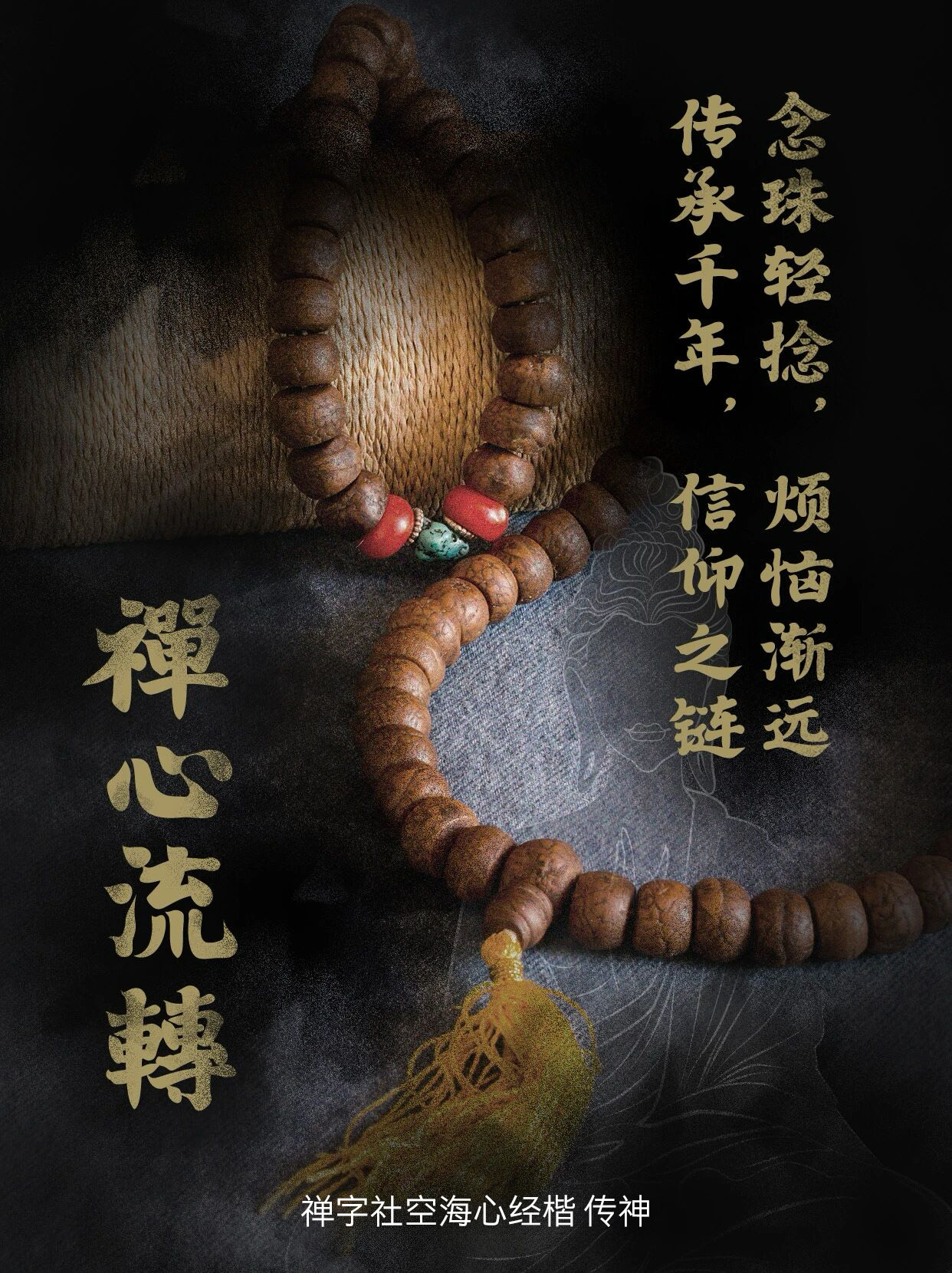
禅字社空海心经楷简繁 传神
唐朝
Zentype-XinJingGBT-Bold
字体名称:
禅字社空海心经楷简繁 传神
书体类型:
楷体
字体语言:
简繁
字体类型:
标准
字符集:
GBT
字体字重:
Bold(大黑)
字形中正,运笔流畅,露锋起笔。转折处圆转与方正并存,展现出单字的丰富多样。各笔画粗细相对统一,进而展现出字体的相对厚度。